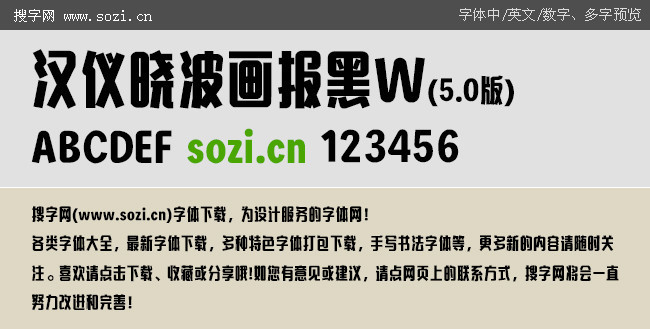
漢儀曉波畫報(bào)黑W5.0
搜字網(wǎng)提供一款漢儀曉波畫報(bào)黑W5.0字體下載,漢儀曉波畫報(bào)黑是一款漂亮的藝術(shù)字體。由漢儀曉波工作室出品,漢儀曉波畫報(bào)黑是一款有著民國美術(shù)字氣息的字體,筆畫干脆利落,毫不拖泥帶水,整體結(jié)構(gòu)高挑挺拔,隱有壯士風(fēng)骨,又具人文情懷。適用于各類標(biāo)題字,海報(bào)設(shè)計(jì),游戲動(dòng)漫設(shè)計(jì),企業(yè)標(biāo)準(zhǔn)字的應(yīng)用。(本字體為個(gè)人非商用版,如需要商用請聯(lián)系漢儀公司購買版權(quán))